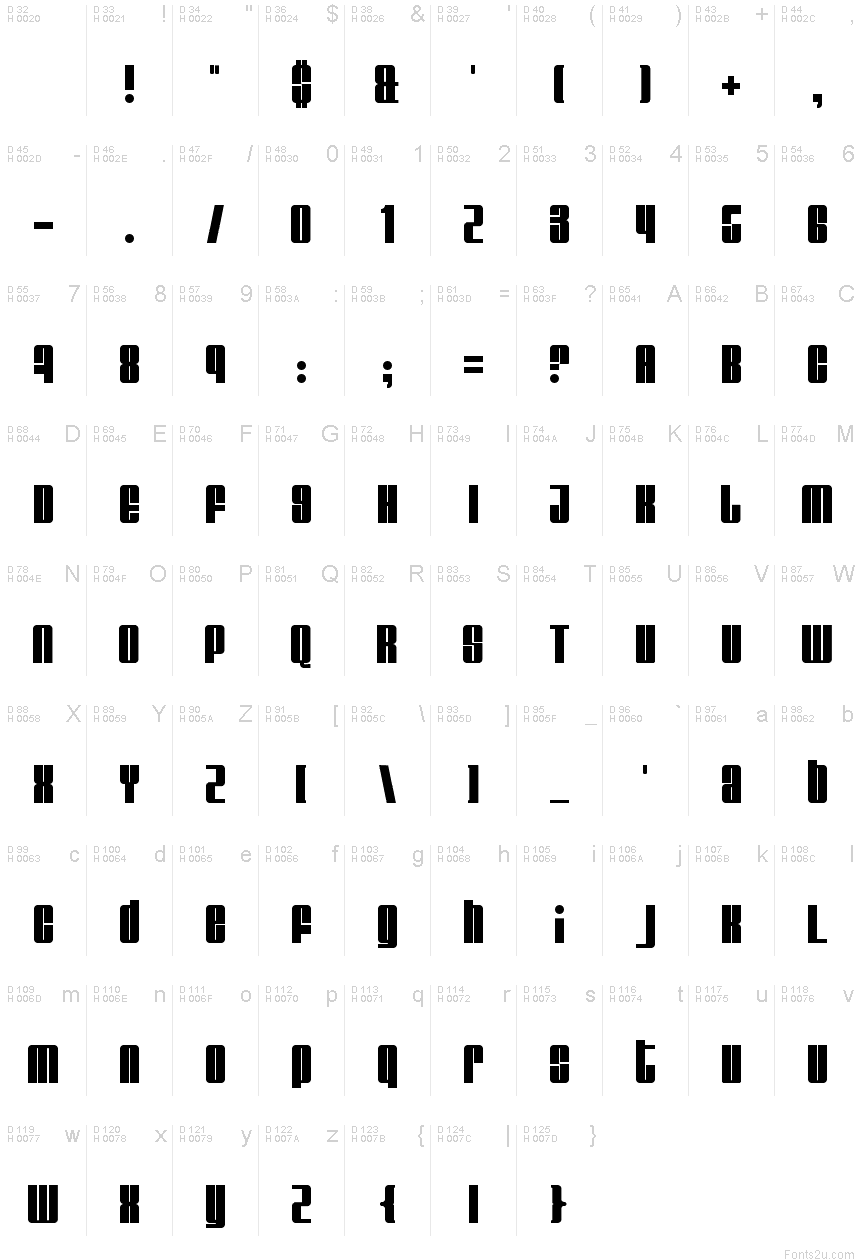
Glare od Dustbust Fonts to darmowy, nowoczesny krój displayowy o wyrazistej, blokowej sylwetce i gładkich, wyciętych detalach, które sprawiają wrażenie maszynowej precyzji. Wysokie, pionowe formy, kanciaste krawędzie i zwarty rytm tworzą solidną bryłę tekstu, która mimo swojej masywności pozostaje elegancka i futurystyczna. Subtelne, inspirowane stylem stencil przerwy nadają Glare mechaniczny, industrialny charakter, dzięki czemu świetnie prezentuje się na ciemnych lub neonowych tłach.
Glare zapewnia wyrazisty, skondensowany wygląd, który przyciąga uwagę na plakatach, okładkach albumów, ulotkach, w grafice gamingowej, logotypach marek streetwearowych i odważnym brandingu. Sztywne kształty zachowują czystość i czytelność nawet w dużym powiększeniu, a miękkie wewnętrzne krzywizny dodają całości osobowości, sprawiając, że krój nie wydaje się surowy. Ten darmowy font doskonale sprawdza się w połączeniu z prostym, geometrycznym bezszeryfem w mniejszym rozmiarze do składu tekstu głównego, pozwalając Glare w pełni zdominować nagłówki.